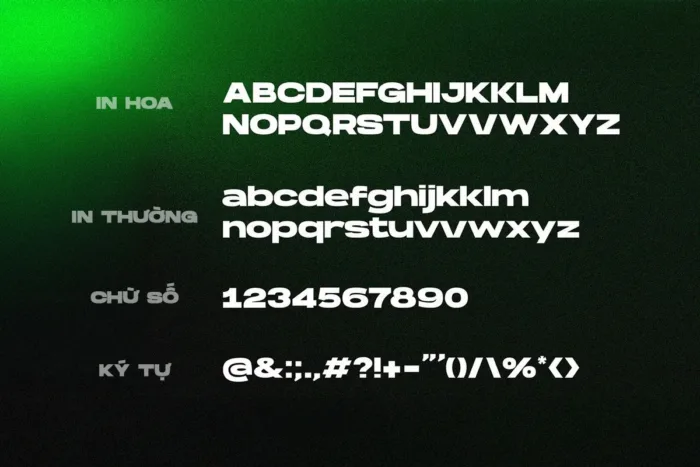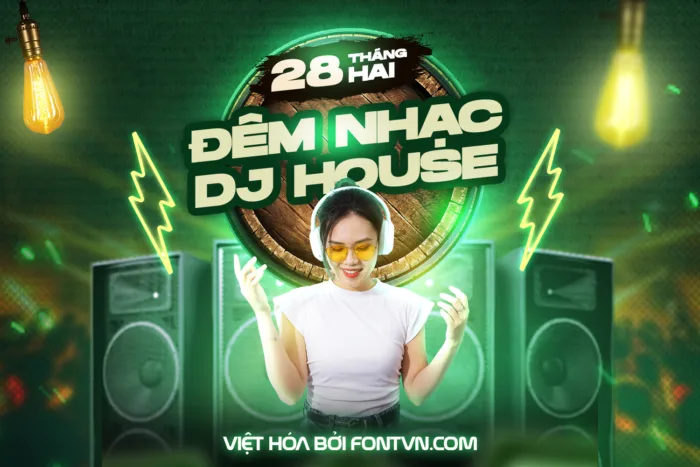
DVN Hanson Việt hóa – Font chữ đậm chất mạnh mẽ và hiện đại
DVN Hanson Việt hóa là một font chữ sans-serif với thiết kế đậm, góc cạnh và đầy uy lực. Với phong cách mạnh mẽ, font chữ này mang lại cảm giác chắc chắn, quyết đoán, phù hợp cho các thiết kế thương hiệu, poster, tiêu đề quảng cáo, áo thun và các ấn phẩm cần sự nổi bật.
Phiên bản Việt hóa của font đã được tối ưu với đầy đủ dấu tiếng Việt, đảm bảo hiển thị đẹp mắt và chuyên nghiệp. Đường nét dày dặn, cấu trúc vững chắc giúp DVN Hanson tỏa sáng trong các thiết kế liên quan đến thể thao, công nghệ, game hay giải trí.